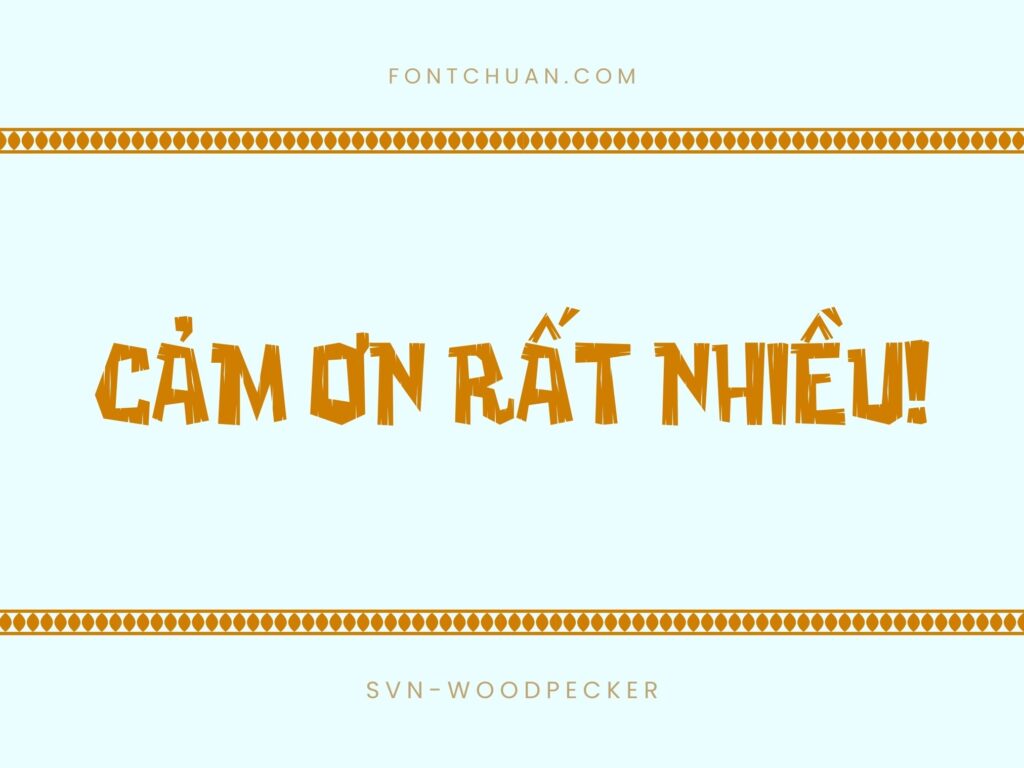
Font SVN Woodpecker Việt Hóa
Tác giả Font: Puguh Sahirul, Semarang, Alexatype
Font SVN Woodpecker là phiên bản Việt hóa của kiểu chữ Woodpecker, được thực hiện bởi STYLEno.1 Fonts. Woodpecker thuộc nhóm Font Decorative, mang phong cách rừng nhiệt đới độc đáo, mô phỏng các tấm gỗ xẻ, tạo cảm giác mạnh mẽ, tự nhiên và sinh động. Font này hoàn hảo cho các thiết kế liên quan đến thiên nhiên, cuộc phiêu lưu hoang dã, trò chơi sinh tồn, poster về rừng và công viên, cùng nhiều ứng dụng sáng tạo khác.
SVN Woodpecker lý tưởng cho các dự án thiết kế yêu cầu sự độc đáo và mạnh mẽ, như thiết kế logo, tiêu đề, bao bì sản phẩm và các ấn phẩm quảng cáo. Các ngành nghề như quảng cáo, ẩm thực và spa có thể tận dụng font này để tạo điểm nhấn trong thiết kế. Ngoài ra, font cũng thích hợp cho các sự kiện như Tết, Giáng sinh, Valentine và các lễ hội khác.